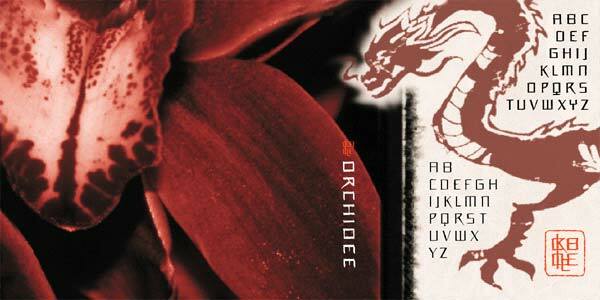
Orchidee Light to bezpłatny krój displayowy w chińskim stylu, którego wąskie, pionowe formy nawiązują do napisu malowanego pędzlem z suchą, poszarpaną krawędzią. Ostre łączenia i gwałtowne zmiany kierunku nadają projektowi wyrazisty, kaligraficzny rytm, dzięki czemu font sprawia wrażenie bardziej ceremonialnego i graficznego niż neutralnego.
Menu restauracyjne, opakowania na wynos, ulotki festiwalowe, plakaty tematyczne i nagłówki witryn sklepowych — to wszystko pasuje tutaj idealnie, zwłaszcza gdy projekt wymaga stylizowanego nawiązania do Dalekiego Wschodu bez uciekania się do dosłownej ilustracji. Krótkie tytuły i etykiety zyskują najwięcej, ponieważ kanciasta tekstura pędzla oraz wysokie, otwarte sylwetki liter nadają każdemu słowu przemyślaną, przypominającą emblemat formę.